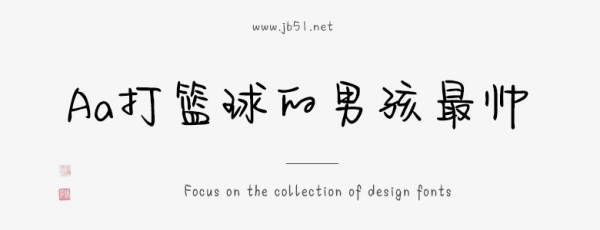
Aa打籃球的男孩最帥是Aa字庫(kù)推出的藝術(shù)字體,字體筆觸略細(xì),書寫流暢 ,具有很好的視覺(jué)感,適合應(yīng)用于藝術(shù)設(shè)計(jì)、平面宣傳設(shè)計(jì)、網(wǎng)頁(yè)設(shè)計(jì),書法字帖等領(lǐng)域,歡迎需要的朋友下載使用。